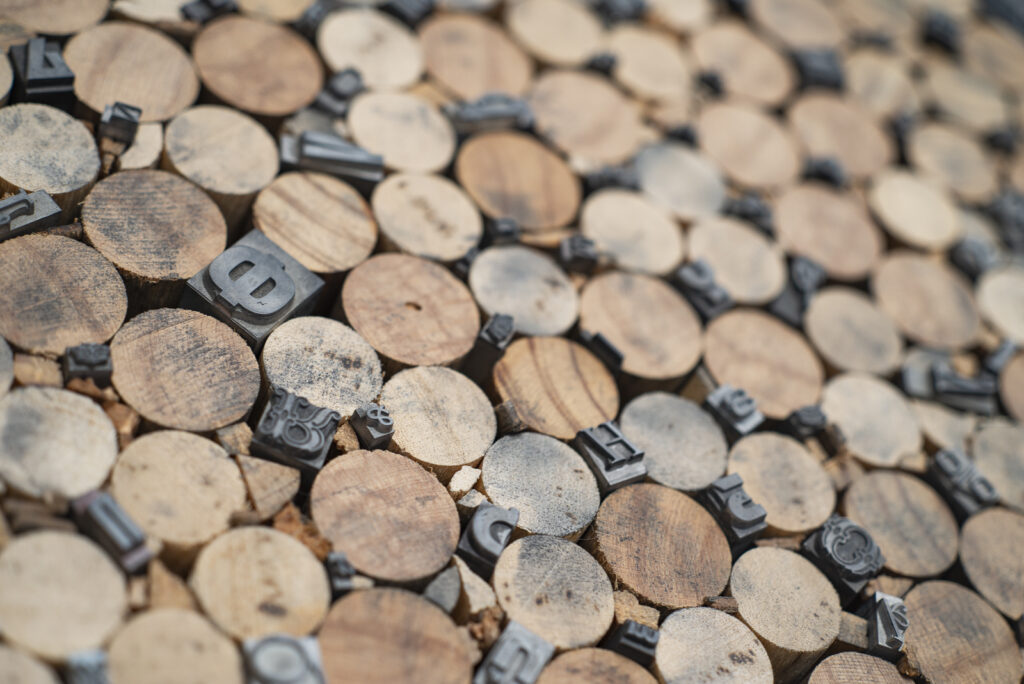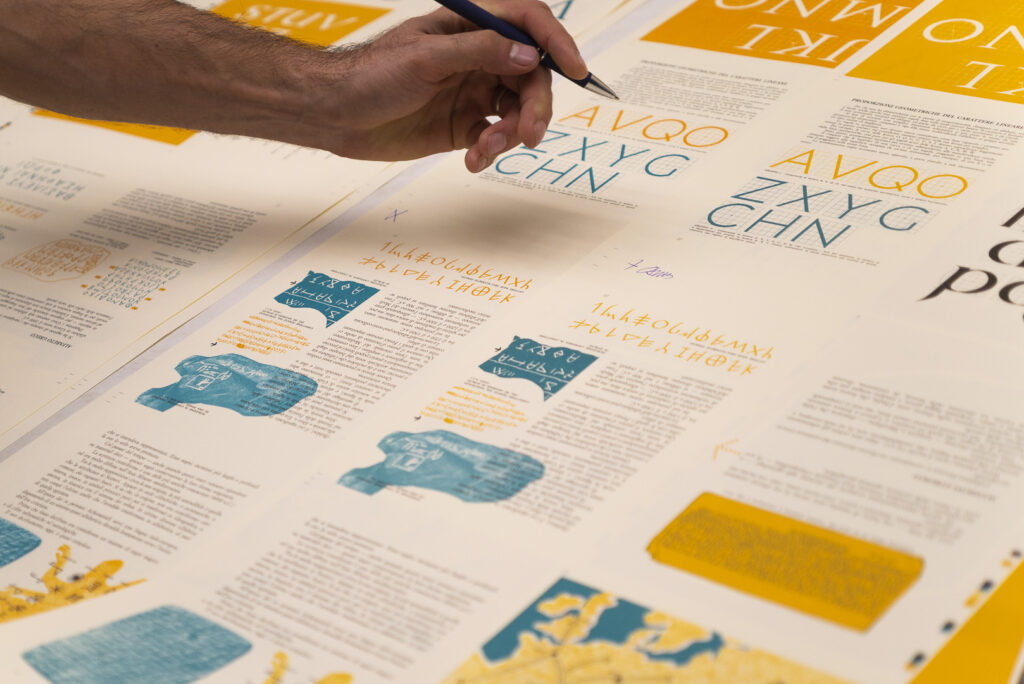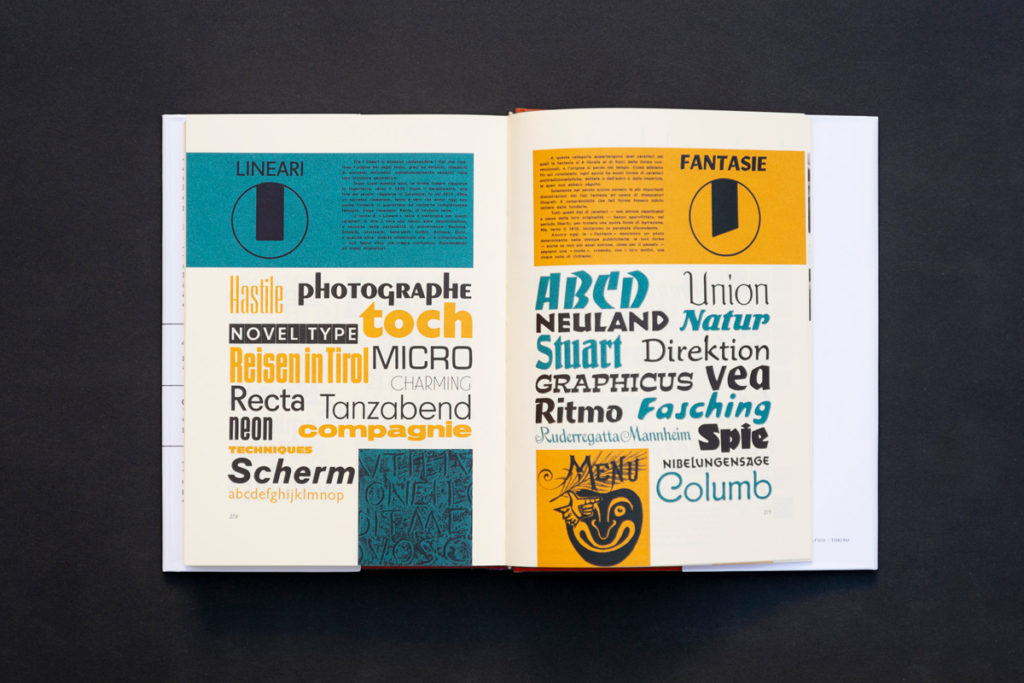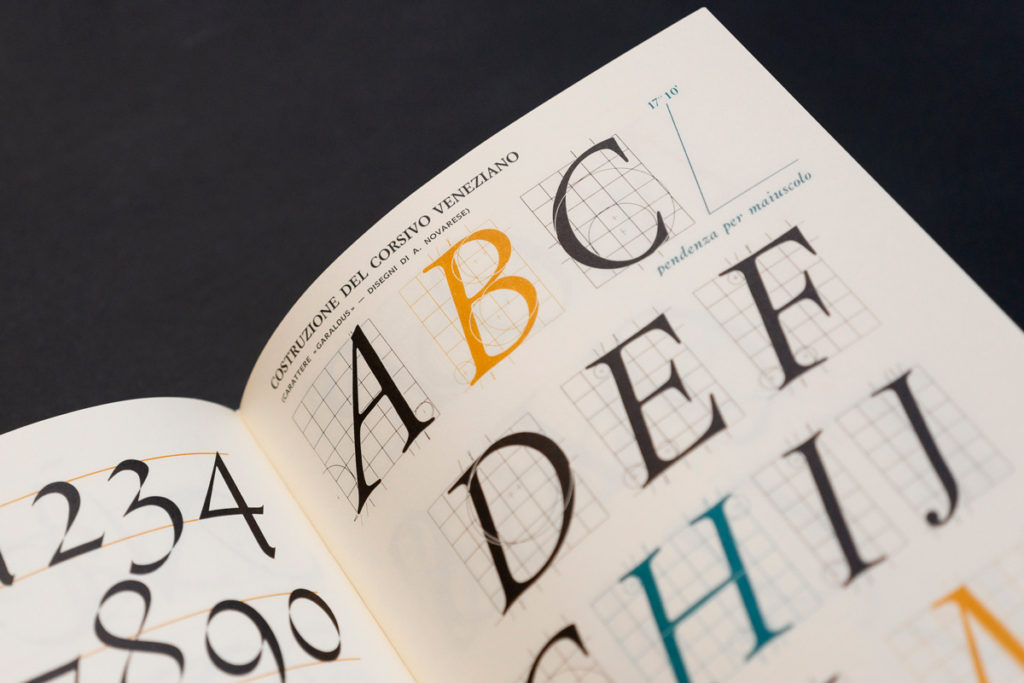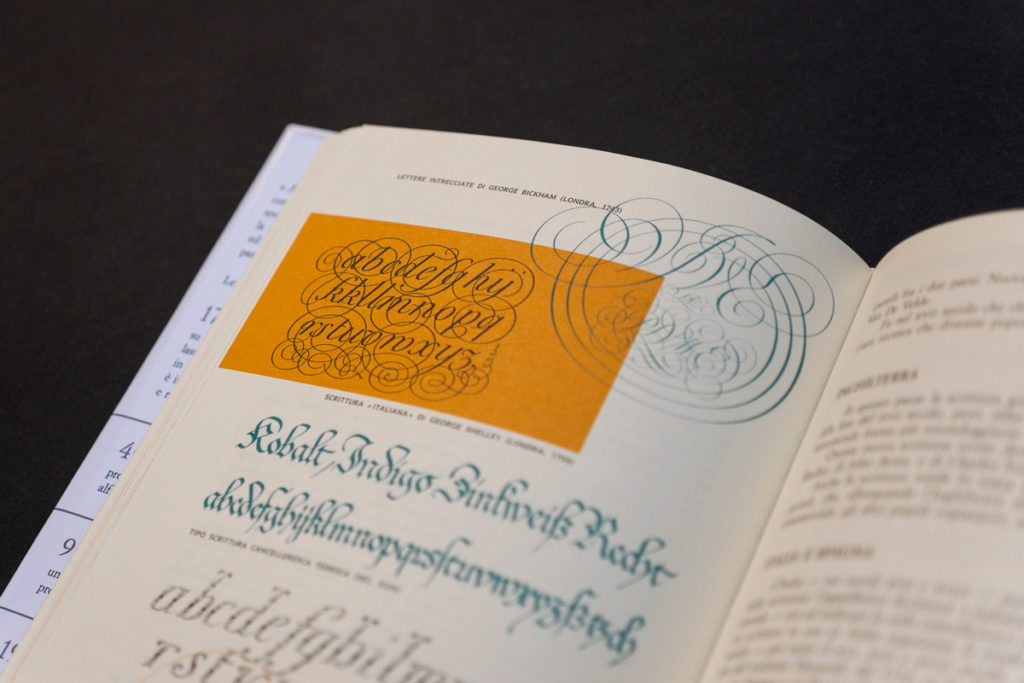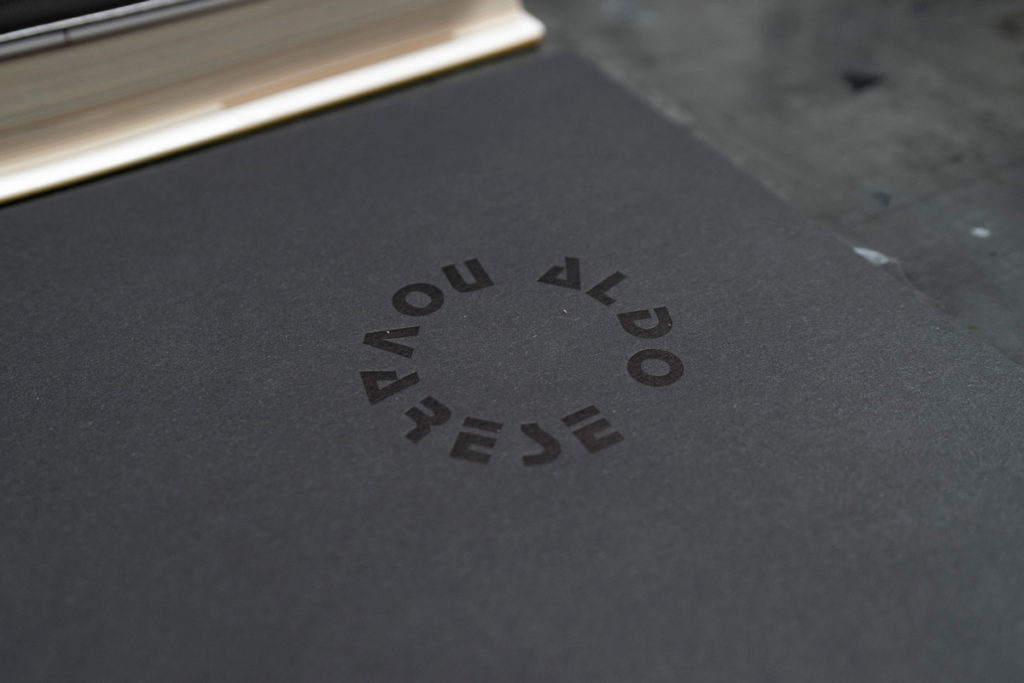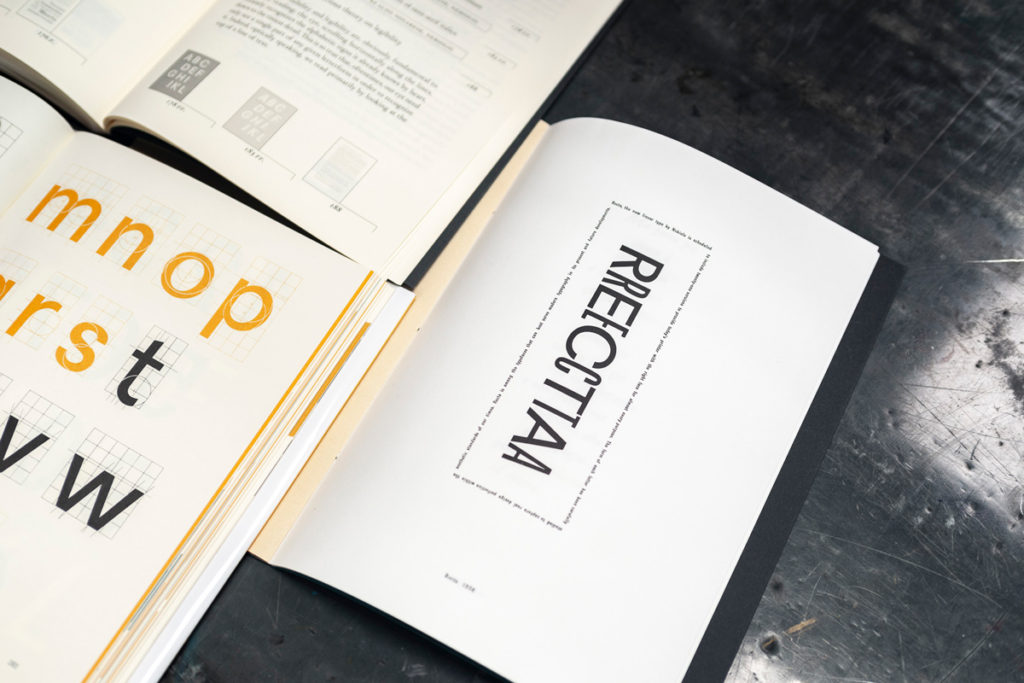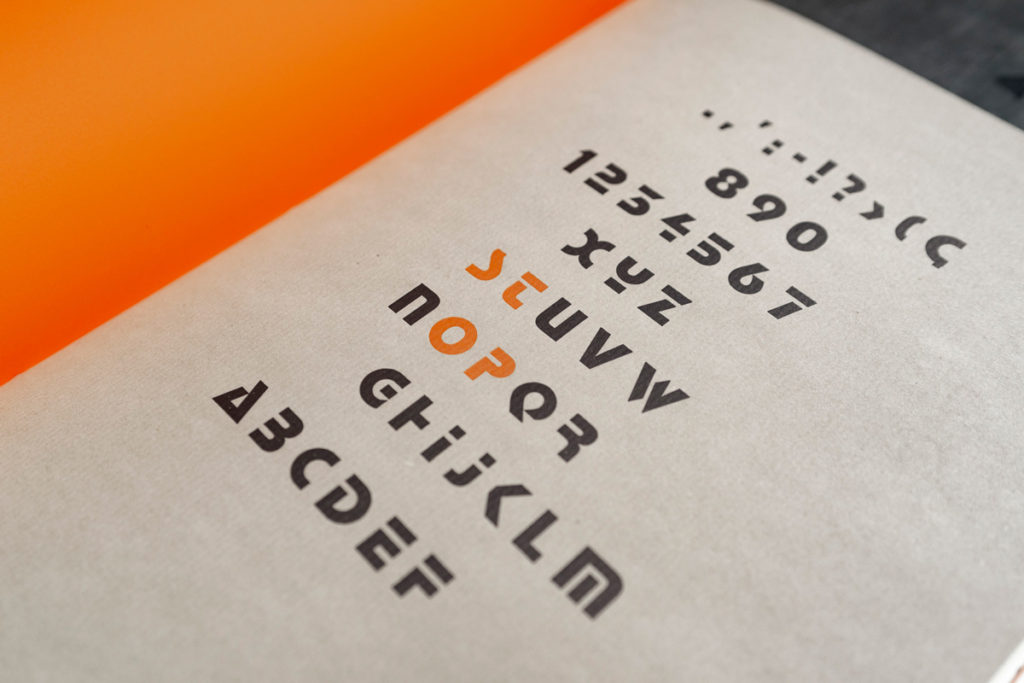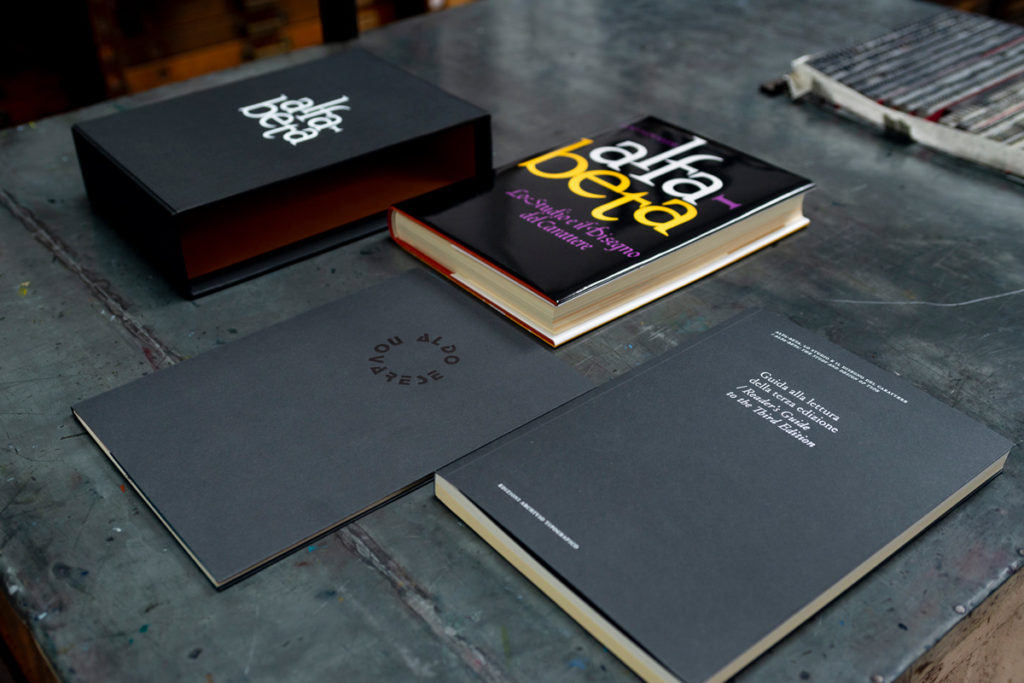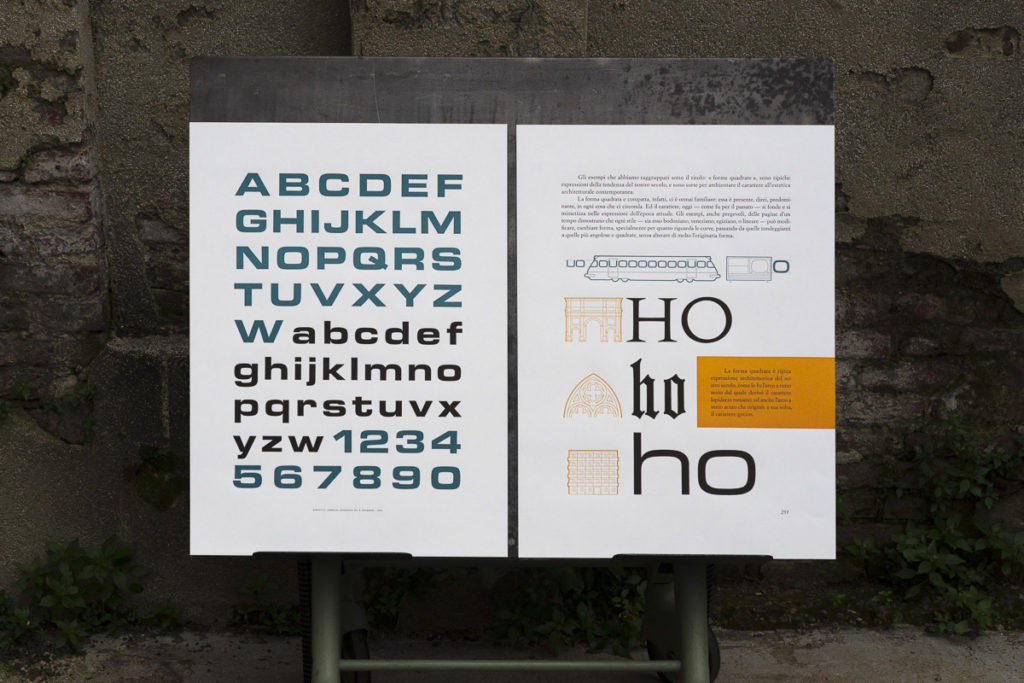
Progetto di riedizione dello storico libro Alfa-Beta, di Aldo Novarese.
La prima edizione di Alfa-Beta, pubblicata nel 1964 da Progresso Grafico e distribuita da G.B. Paravia & C., costava 5.000 lire. Questo libro è una testimonianza dell’opera complessiva e dell’ethos progettuale di Aldo Novarese. Si tratta di una visione estremamente specifica della disciplina, scritta da un professionista, che descrive l’evoluzione della scrittura.
Oltre a essere uno dei pochissimi manuali di teoria e pratica del type design scritti in italiano, Alfa-Beta presenta anche la storia della tipografia da una prospettiva originale e dinamica, che deriva dal suo personale metodo di disegno e progettazione. Pertanto rimane una fonte di ispirazione degna di nota.
Aldo Novarese, nato a Pontestura, in provincia di Vicenza, il 29 giugno 1920, raggiunse la fama mondiale per i suoi straordinari caratteri tipografici. Nel 1936, all’età di sedici anni, iniziò a lavorare presso la Nebiolo, una fonderia di caratteri in piombo e una fabbrica di macchine da stampa, sotto la guida di Alessandro Butti. Nel 1952 successe a Butti come direttore dello studio di progettazione interno. La sua carriera in Nebiolo durò fino al 1975, contestualmente al declino della produzione di caratteri mobili in piombo.
Il punto di partenza della riedizione è stato il rinvenimento da parte di Piergiuseppe Molinar delle pellicole originali utilizzate per la seconda ristampa, del 198X. Archivio Tipografico, con Lorenzo Bolzoni e Matilde Argentero, nipote di Novarese, hanno concepito e curato il progetto intorno alla riedizione del libro.
Alfa-Beta è stato riedito come edizione anastatica, accompagnato da una guida alla lettura che contiene la traduzione in inglese del libro con tre saggi bilingue introduttivi alla persona e all’opera di Aldo Novarese e una nota della traduttrice Alta L. Price. I libri sono stati stampati in offset da Grafiche Antiga. Una versione deluxe del libro contiene anche uno specimen composto internamente con caratteri di piombo disegnati dall’autore. La custodia rigida della versione deluxe è stata realizzata da Bottega Fagnola.
In occasione della campagna sono stati prodotti altri elaborati che completano il lavoro di recupero dell’opera di Novarese: un dittico di poster che rappresentano due delle pagine più rappresentative di Alfa-Beta, un manifesto che reinterpreta la produzione tipografica di Novarese e infine una riproduzione digitale del Nova Augustea, carattere impiegato sulla copertina di Alfa-Beta.
Il progetto di riedizione è stato finanziato tramite una campagna Kickstarter in occasione del centenario della nascita di Aldo Novarese (29 giugno 2020).